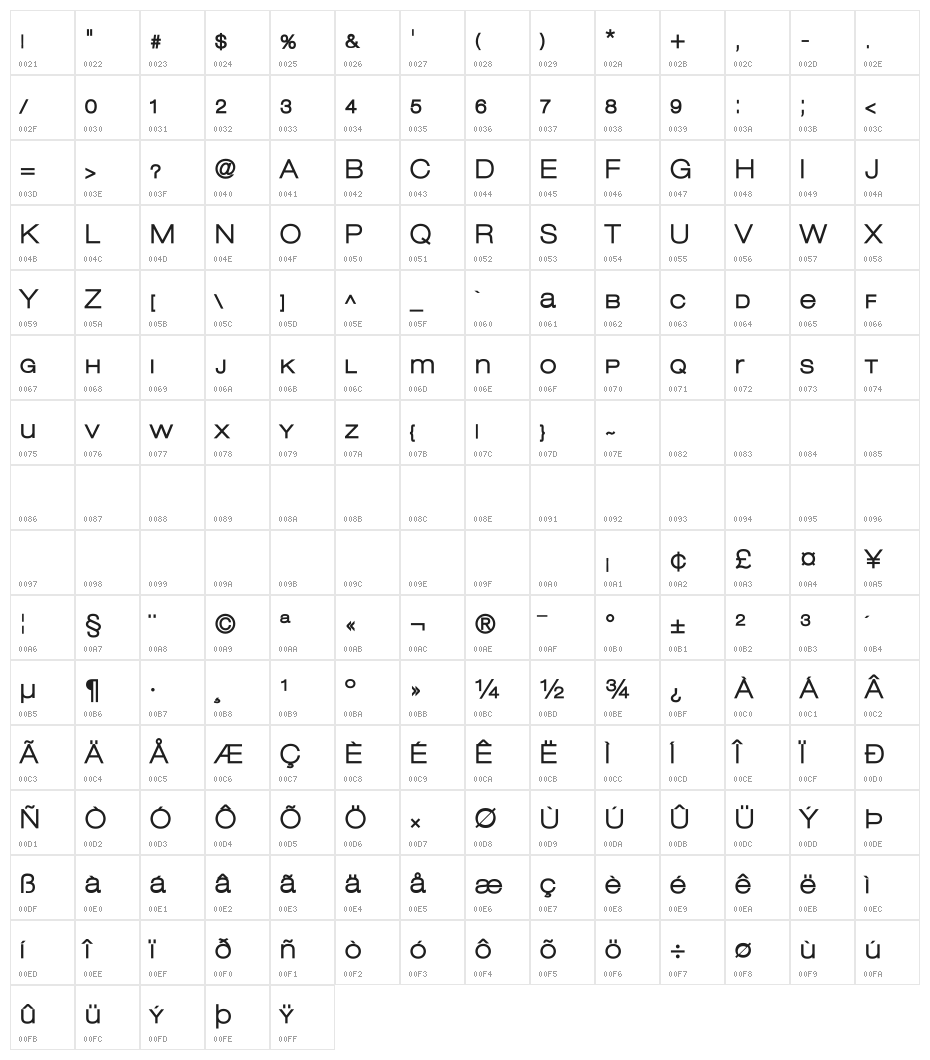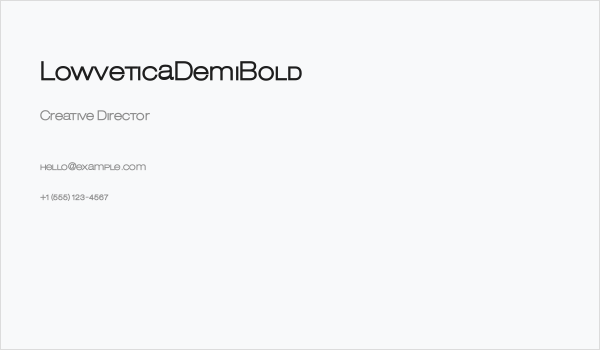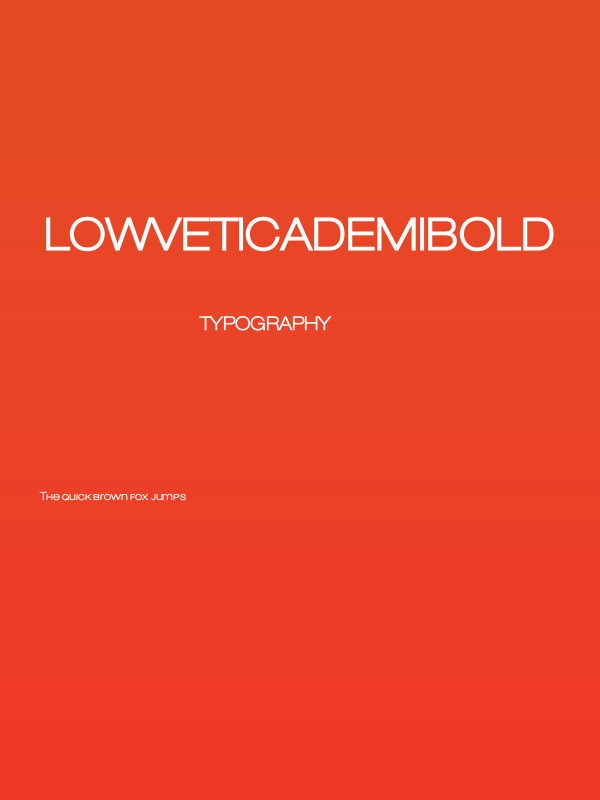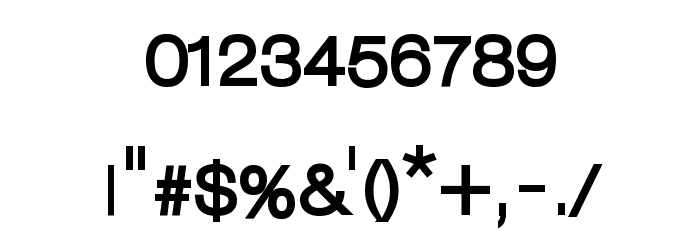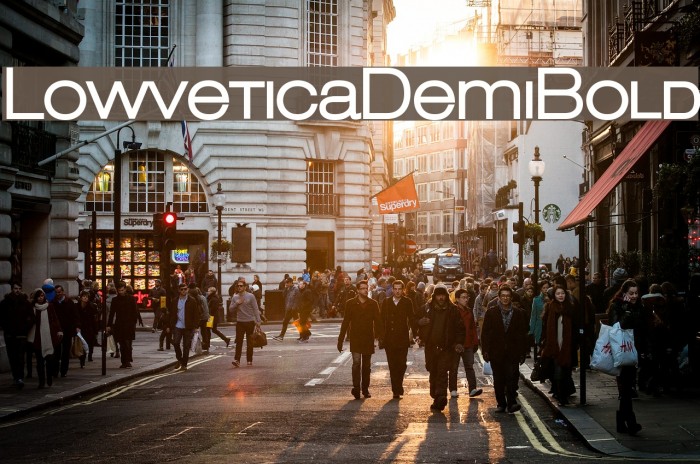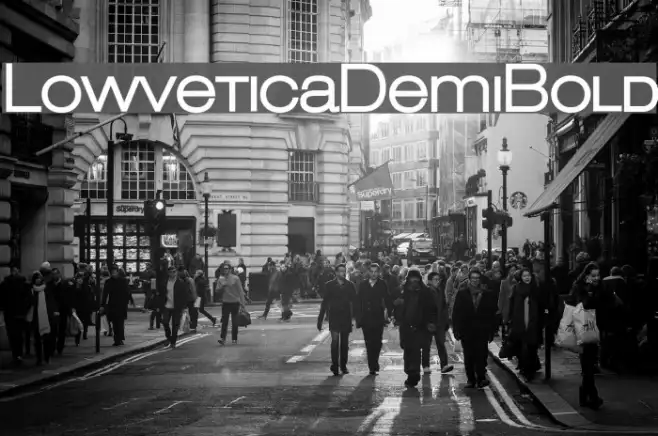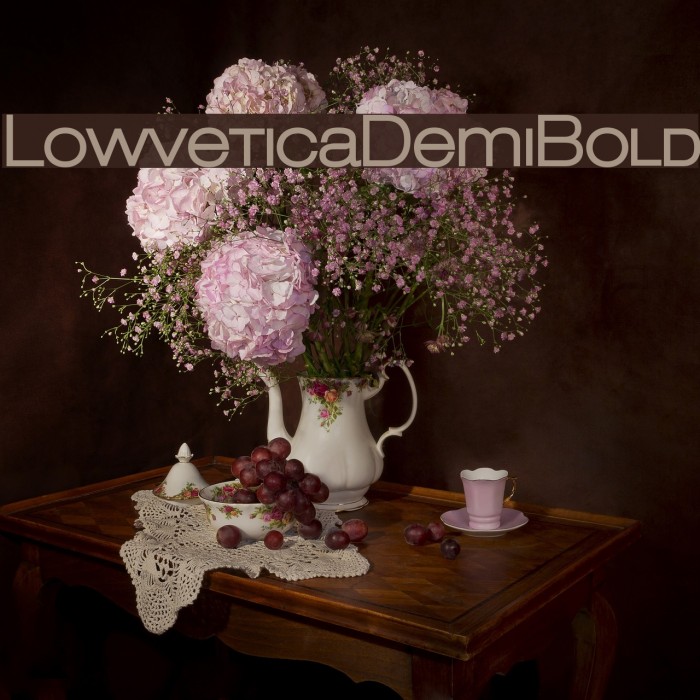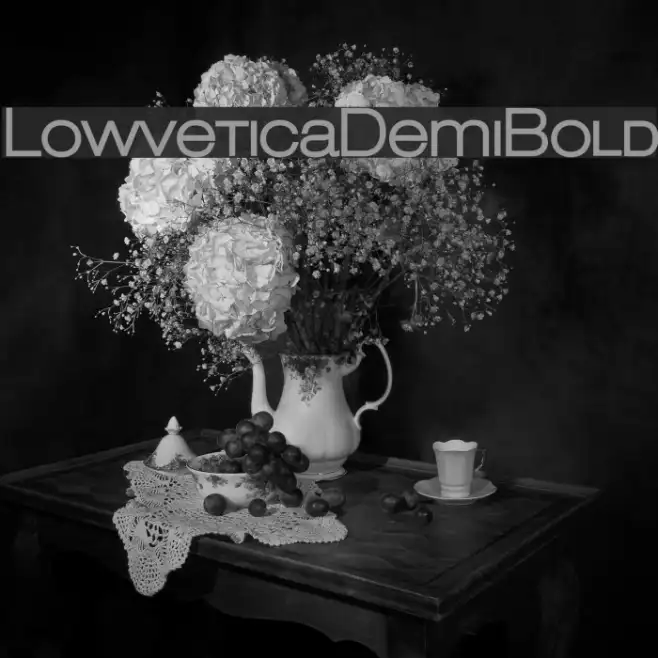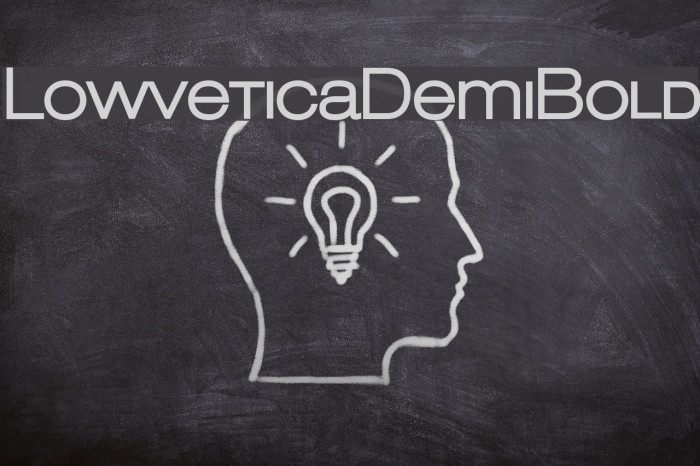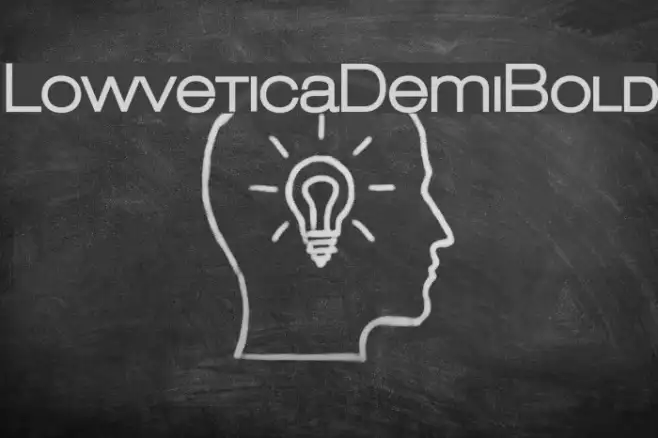
LowveticaDemiBold Font
| Projets proposés | Ideal for branding, web design, advertising, and editorial layouts due to its clarity and modern appeal. |